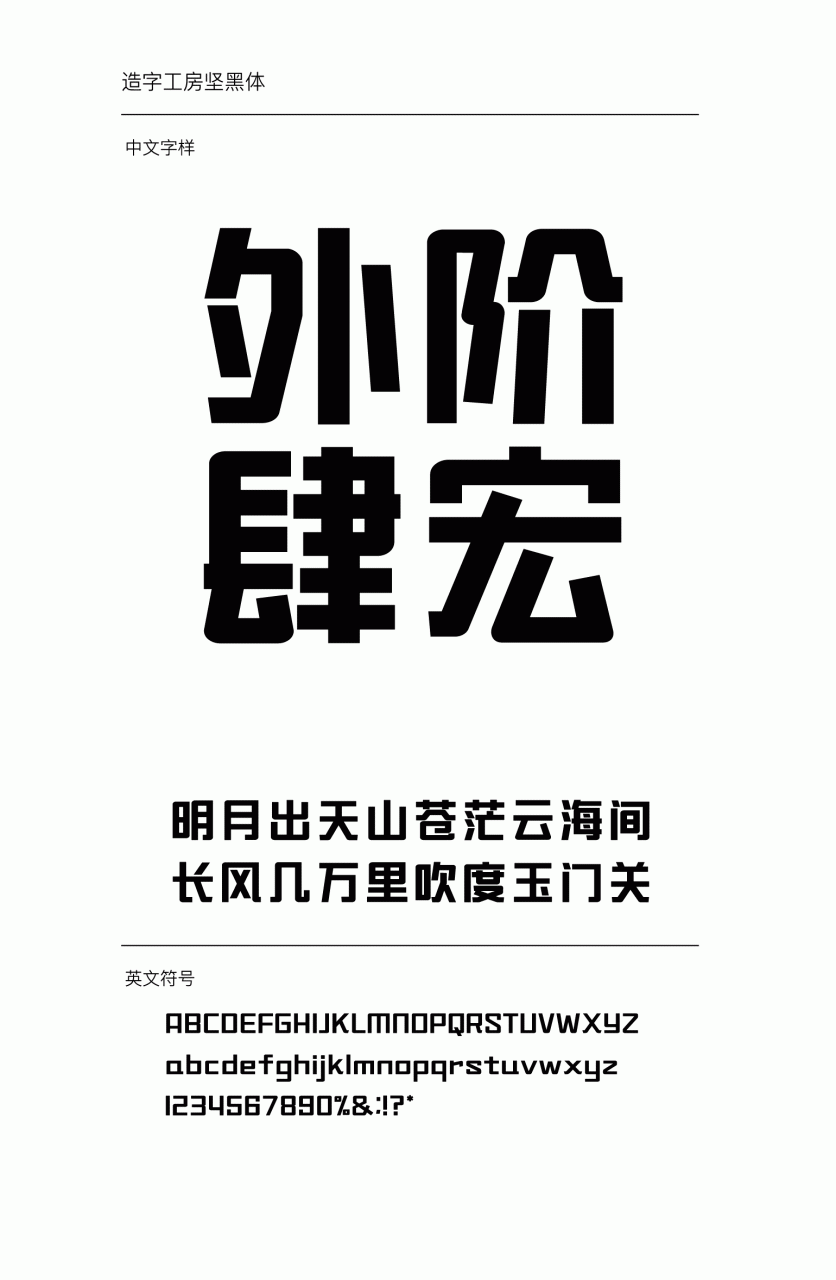
造字工房坚黑常规体设计说明
造字工房坚黑体,结构端正、字形饱满、笔画匀称,字形整体风格刚劲有力而不失俊儒之风,其笔画中蕴含古朴沉厚端凝之势。在主副标题与品牌宣传上有很大的应用空间。 本字体为简体字库,采用OpenType/CID格式,Adobe-GB1-5编码。基于中华人民共和国GB2312-80字符集标准,另按需添加101个汉字。共收容字数6864CJK汉字,ASCII常用字符100个。